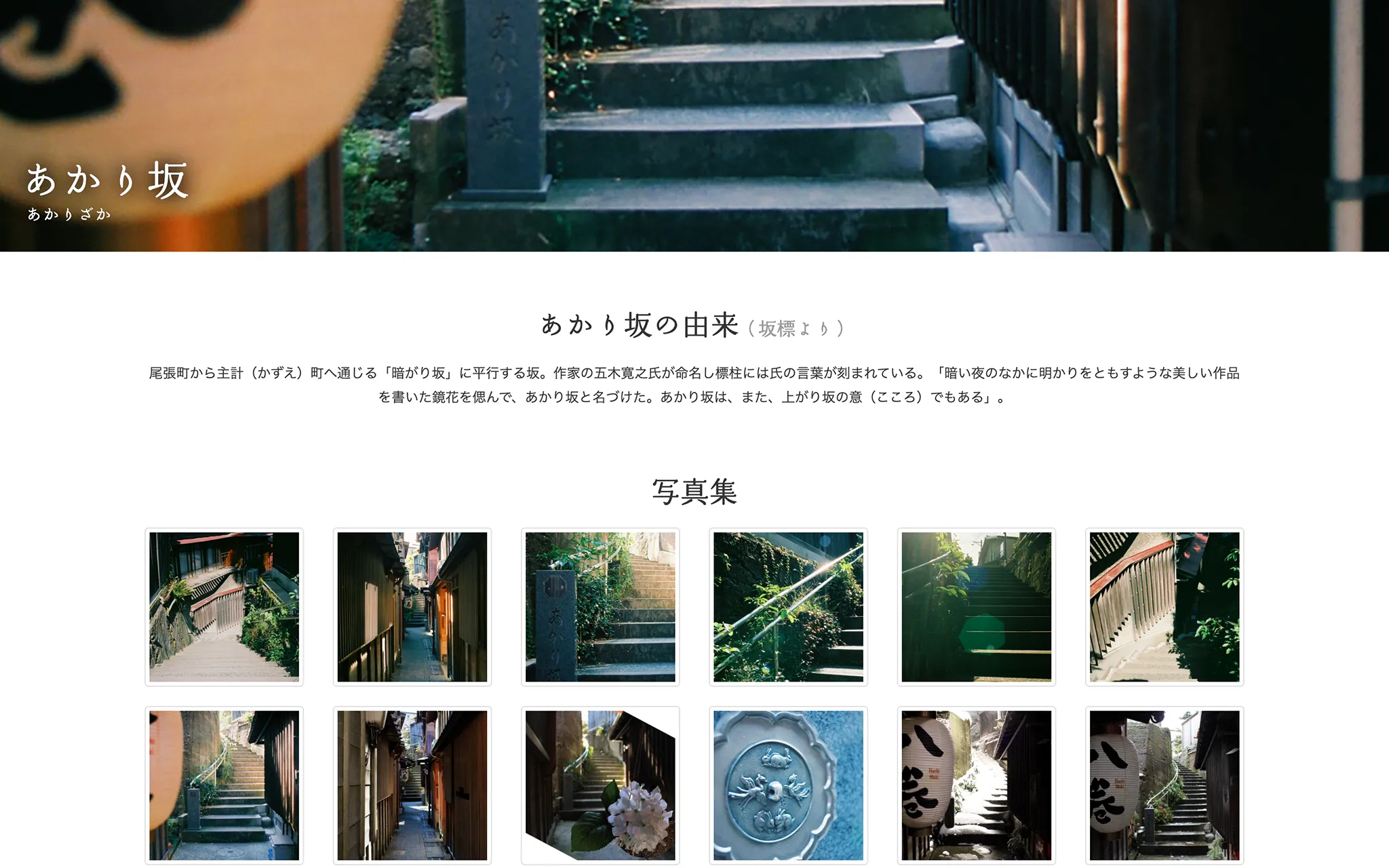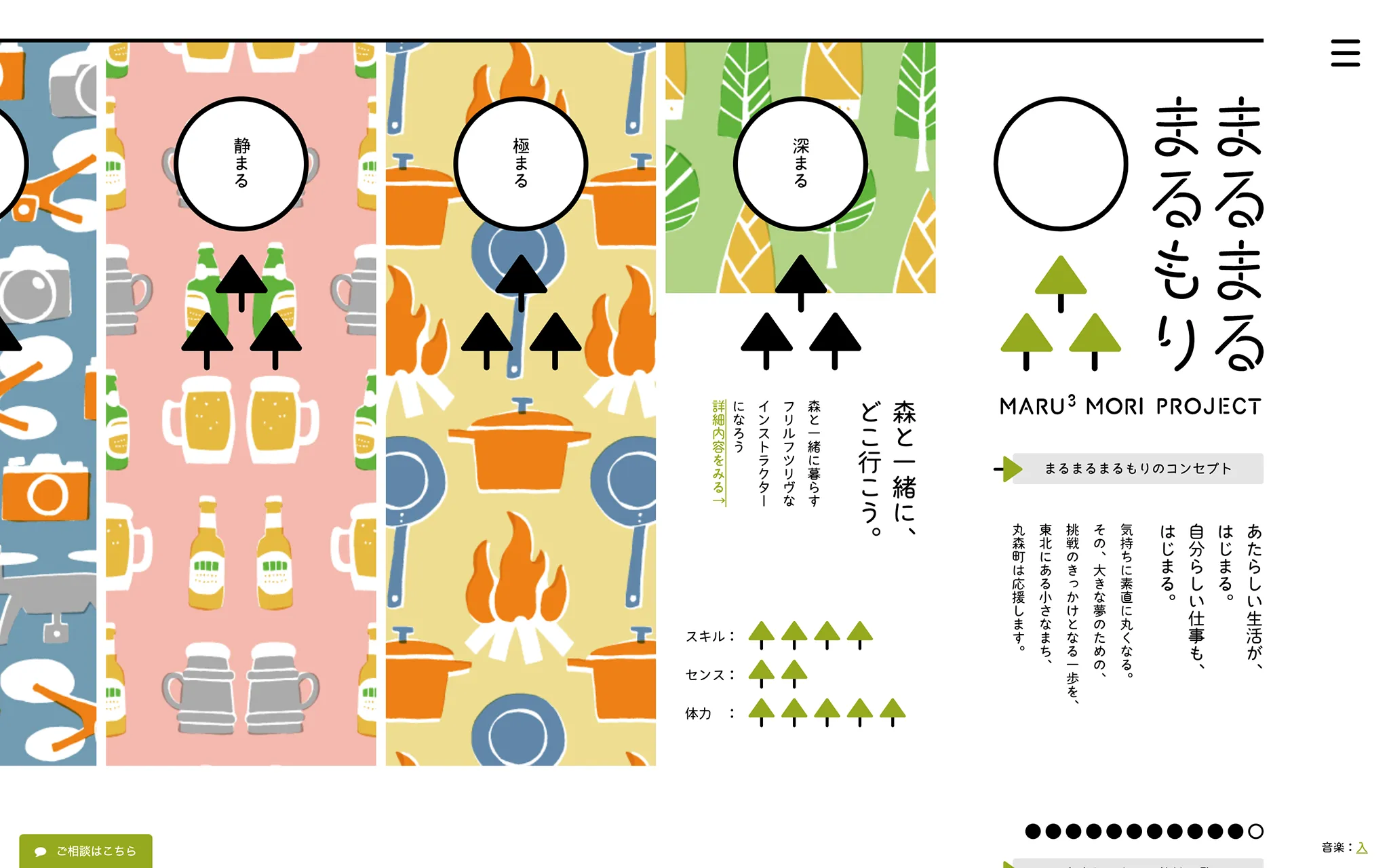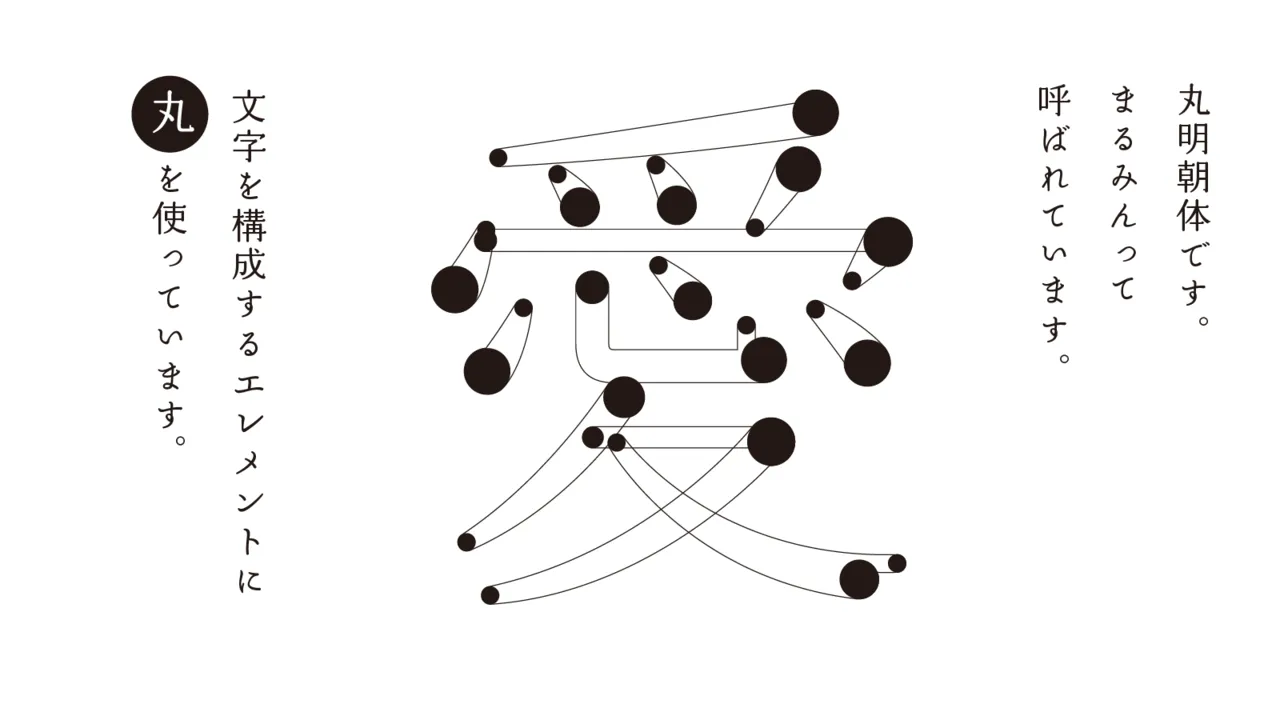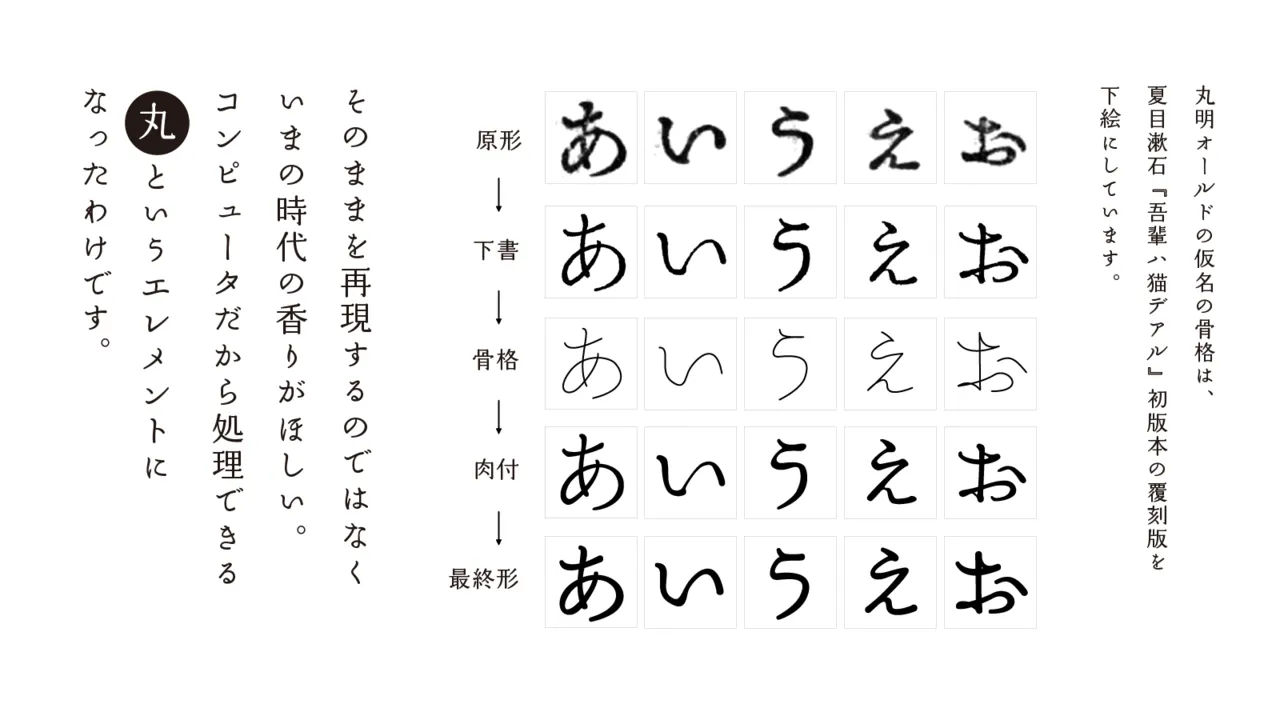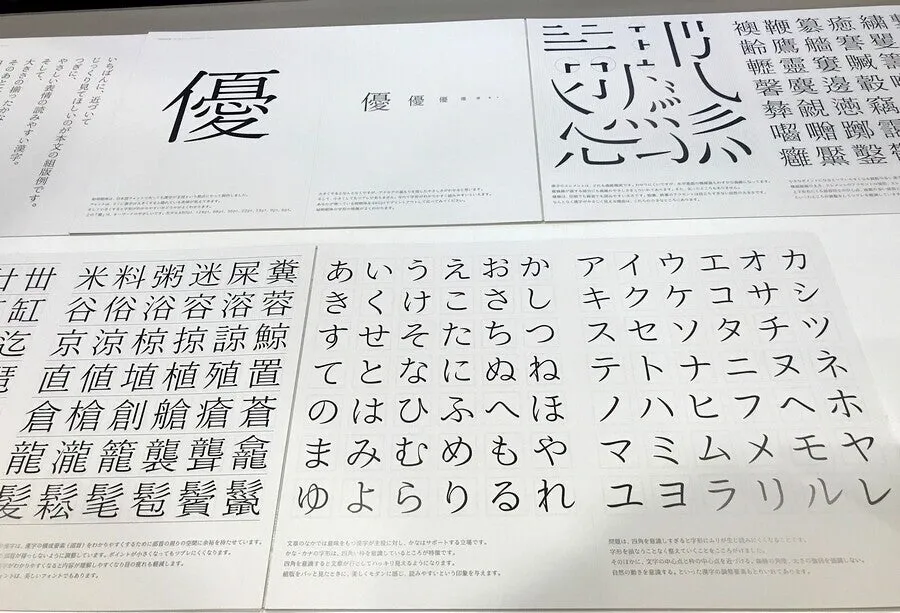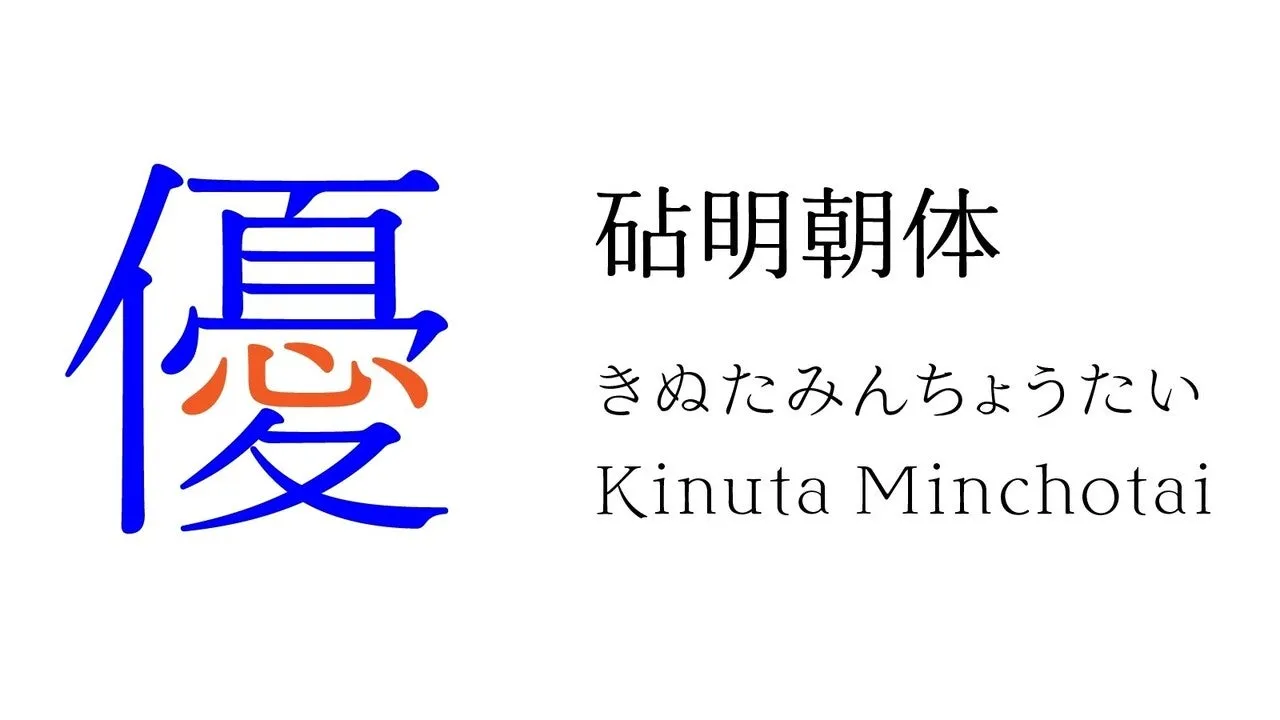
20年以上広告で使われ続ける「丸明オールド」。そして、新書体「砧明朝体」で新たなステージへ――砧書体制作所(旧カタオカデザインワークス)
砧書体制作所
皆さんは、砧書体制作所というフォントメーカーをご存じでしょうか? 20年以上にわたり、広告やパッケージなどで使われ続け、街中で毎日見かけることができる書体、「丸明オールド」を生み出したフォントメーカーです。
2016年1月に、カタオカデザインワークスから砧書体制作所に社名変更したので、「カタオカデザインワークス」の社名で覚えている人もいるかもしれませんね。創業は1995年ですので、砧書体制作所も比較的新しいフォントメーカーになるかと思います。
この20年間、たくさんの素敵なフォントを世の中に提供している書体デザイナーが、片岡朗さんと木龍歩美さんです。
「丸ゴシック体」は聞いたことあります。でも、「丸明朝体」って?
ゴシック体には、大まかな分類として、角ゴシック体と丸ゴシック体があります。でも、丸明朝体ってあまり聞いたこと、ありません。丸明朝体って書体分類、ありましたっけ?
はい、あります。砧書体制作所が2001年にリリースした「丸明オールド」が丸明朝体の代表選手です。ここでは、丸明朝体とは「トメやハネやハライ等の要素が丸く処理がされた明朝体」と定義することにしましょう。
20年前にリリースされた丸明オールドは、フォント業界をあっと驚かせた今までに無かった書体でした。それまで、明朝体といえば、ウロコが三角の形をして伝統的なイメージの明朝体が当たり前でした。
ところが、丸明オールドは、すべての要素が丸いのです。ウロコだけでなく、始筆部分も、トメもハネもハライも、全て丸のエレメントで構成されています。このスタイルが、文字に柔らかさと優しさを感じられるのだと思います。
そして、ひらがなとカタカナが、活版印刷時代の書体の骨格で作られているので、懐かしさも感じられるのです。
当たり前という概念を払拭しつつ、明朝体の骨格や日本の活字文化も継承し、何年もの時間をかけて作り上げられたフォントには魂が宿るのです。
毎日、街中で見かける丸明オールドですが、誕生から20年経っても使われ続けています。見慣れてしまうと飽きてしまうのが一般的ですが、この書体には、不思議な魅力があるのだと思いました。
その後、2007 年に仮名を6種追加し、「丸明朝体ファミリー」として拡張されました。
「丸明朝体」以外にも、丹精込められた、たくさんのフォントが誕生
砧書体制作所のフォント制作アトリエに何度かお伺いしたことがあります。康熙字典や明治時代に刊行された夏目漱石の書籍などなど、活字や書体が好きな人にとって、参考になる図書がたくさんありました。そして、制作過程のフォントの印刷見本が壁に綺麗に貼られています。そんなアトリエで、この20年間、たくさんの素敵な書体が誕生しました。
片岡朗さんの経歴をご紹介しつつ、書体リリースの変遷もご紹介します。
片岡朗さんは1947年生まれ。東京都出身。高校卒業後、レタリング事務所、デザインプロダクション、広告代理店を経て1990年独立。
| 1972年 | 第2回写研主催タイプフェイスコンテスト3席受賞 |
|---|---|
| 1995年 | 有限会社カタオカデザインワークス設立 |
| 2000年 | サントリーモルツの広告キャンペーンで「丸明オールド」発表 |
| 2005年 | 12種のかなの形の差をファミリーとした「iroha gothic family」発表 |
| 2007年 | 6種のかなのバリエーションを加えた「丸明朝体family」発表 『文字本』誠文堂新光社より上梓 |
| 2009年 | 角丸の差で2種の漢字を使い分けられる「丸丸ゴシック」発表(日本タイポグラフィ年鑑大賞受賞) |
| 2012年 | コラボレートフォント、筆書体「佑字」発表 オーダーフォント「どんぐり」発表 |
| 2013年 | コラボレートフォント、手描き文字「山本庵」発表 |
| 2014年 | 極細フォント「芯」発表 |
| 2016年 | 屋号を砧書体制作所に変更 |
| 2017年 | 「砧明朝体」発表(日本タイポグラフィ年鑑大賞受賞) |
| 2018年 | 「砧明朝体 L」をリリース |
| 2020年 | 「砧明朝体 R/B」をリリース |
「砧明朝体」という新しい書体
2018年5月11日に、竹尾の見本帖本店で開催された「日本タイポグラフィ年鑑2018グランプリ」受賞記念スペシャルトークショーに参加しました。登壇者は、グランプリを受賞した砧書体制作所の片岡朗さんと木龍歩美さんです。
毎年、国内外からタイポグラフィ・デザイン作品が応募され、『日本タイポグラフィ年鑑』に受賞作品や入賞作品が収められます。この年は1,374件の作品が応募され、お二人が制作した「砧明朝体」がグランプリを受賞されたのです。
グランプリ受賞を祝福したくて、最前列に座って片岡さんと木龍さんのお話をじっくりお聴きしました。
思い返すと、4~5年前に片岡さんにお会いした際、「自分の明朝体を探す旅に出ます」とお聞きしていました。そして、3年以上の歳月をかけて、砧書体制作所として、新しい明朝体を誕生させたのです。その新書体のコンセプトは、「優しさ」と「間」だそうです。
砧明朝体は、曲線の要素を多く取り入れたそうです。それが、印刷のにじみ効果のようになり、見る人に対して優しさを感じさせるようです。そして、横棒と縦棒にも、曲線を取り入れているので、よく見ると直線ではないのです。
片岡さんからお聞きして、印象に残ったフレーズをご紹介します。
写植時代には、1mmの幅の中に手描きで10本の線を書くという技術が必要とされた。いまはMacで書体を作れるけど、その感覚を大事にすることが重要なのです。画数の多い字を縮小しても潰れないように作る際に必要な処理です。そして、仮名は曲線がもともと美しい書体なので、漢字との調和を保つよう、制作しました。
トークショーの会場で、片岡さんに質問をさせていただく機会をいただきましたので、
片岡さんと木龍さんが手掛ける書体には優しさと温もりを感じます。そして使い続けても飽きがこないのは凄いなぁと感じます。
質問です。砧明朝体のアルファベットはとても個性があります。A、B、K、N、Q、Rとかg、k、!、?、&、6、9など。今まであまり見たことのない形をしていると思います。でも組んでみると違和感がありません。最初からこの形が思い浮かんだのか、試行錯誤の中から誕生したのでしょうか?
とお聞きしてみました。
片岡さんの回答は、こうでした。
欧文書体はものすごい数の書体が存在し、綺麗な書体がすでにたくさんあります。日本語書体を制作しているので、欧文書体の美しさを求めるというより、和文と欧文とを組み合わせたときに、こういったアルファベットもあってもいいじゃないかなと思ったんです。漢字や仮名の要素を欧文に流用したのは実験的でもあり、みなさんが、これからどう感じていくのだろうかと興味があります。
片岡さんは、フォントの利用者に対して、書体をどう表現するかの選択肢の提案をしているのだと思いました。
うれしいことに、セミナー会場で、アートディレクターの副田高行さんが聴講されていました。副田さんは、丸明オールドがまだ制作過程のリリースしていないときの2000年に、丸明オールドを使ったサントリーモルツの新聞広告を発表しました。その後、20年間以上、丸明オールドは、飲み物や食品、化粧品の広告になくてはならない存在になったのです。
新書体に対する評価はリリースされた時の反響だけでなく、何十年、何百年経ってからの評価で見えてくるものがありますよね。ファッションと同じように、書体の評価も時代と共に変化するものなのかもしれません。
砧書体制作所の書体ご紹介
砧書体制作所からリリースされている代表的なフォントを、FONTPLUSためし書きで表現してみました。
砧書体制作所のフォントを活用した導入事例
Webフォントとして活用した導入事例を2つ紹介します。
金沢の坂道は、Webサイトの雰囲気と優しさを感じる丸明オールドとの相性がとても良いです。コンテキスト(サイトコンセプトや情景)に合わせた書体選びが秀逸です。
まるまるもりもりプロジェクトは、Webサイトでは難しいと言われていた「たてよこ混在のレイアウト」も、うまく活用し、楽しくて美しいサイトに仕上がっていますね。
砧明朝体など、砧書体制作所のフォントを使った、表現豊かなサイトに出会えるのがこれからも楽しみです。